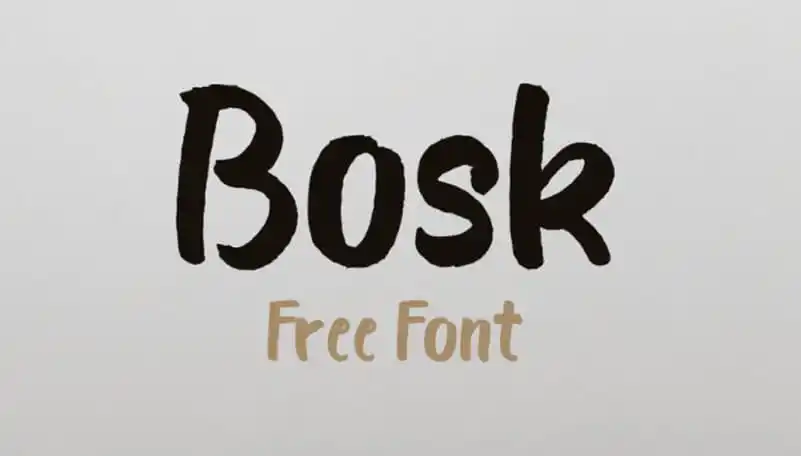
Bosk Brush Font – Download Grátis
A Bosk Brush Font é uma elegante fonte brush que traz a sofisticação do estilo autêntico dos cadernos manuais. Seu design foi criado pelo designer Hamilton, resultando em linhas suaves e expressivas, perfeita para criar texturas interessantes em qualquer tipo de projeto gráfico. Esta fonte é ideal para aqueles que procuram um toque de elegância moderna junto com a sensação autêntica do desenho à mão livre. A Bosk Brush Font oferece uma variedade de opções, desde linhas suaves e leves até formas mais contidas e rítmicas, tornando-a versátil para diversos usos em logotipos, headlines e design editorial. Adicionar esta fonte a seu arsenal vai transformar suas criações digitais num ato de autenticidade contemporânea.